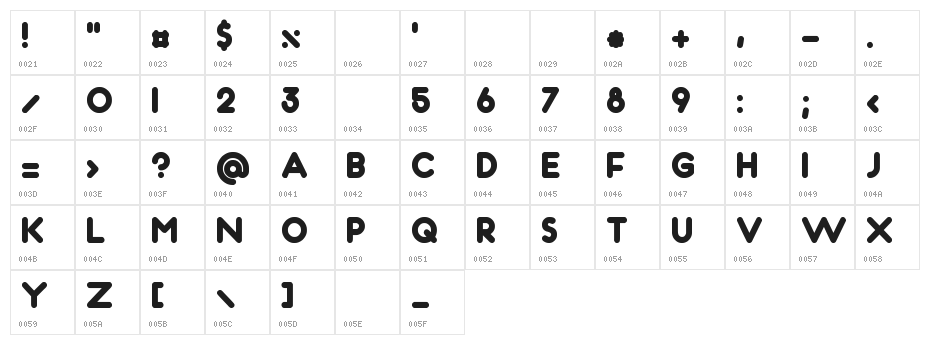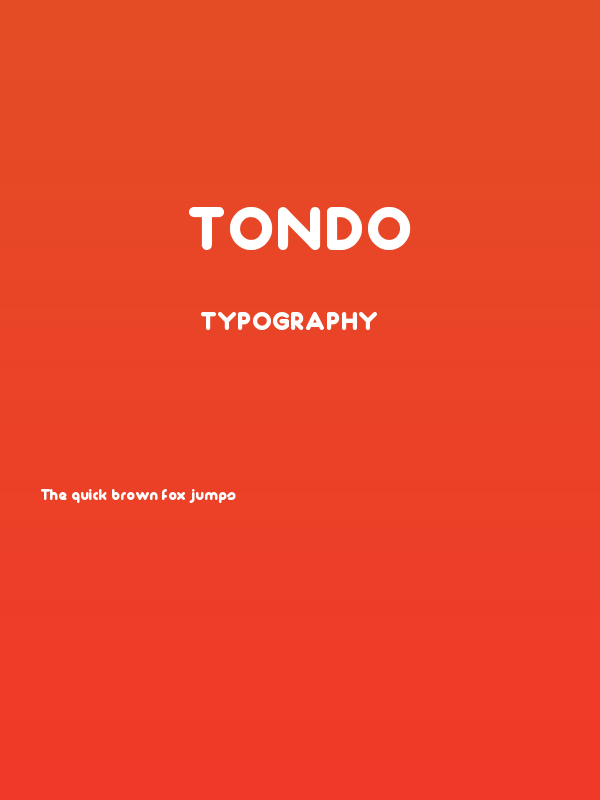
Tondo Font
| Название | Tondo |
| Категория | Web 2.0 |
| Область применения | Headlines, Logos, Informal Text |
| Рекомендуемые проекты | Ideal for children's books, playful branding, casual invitations, and friendly advertising. |